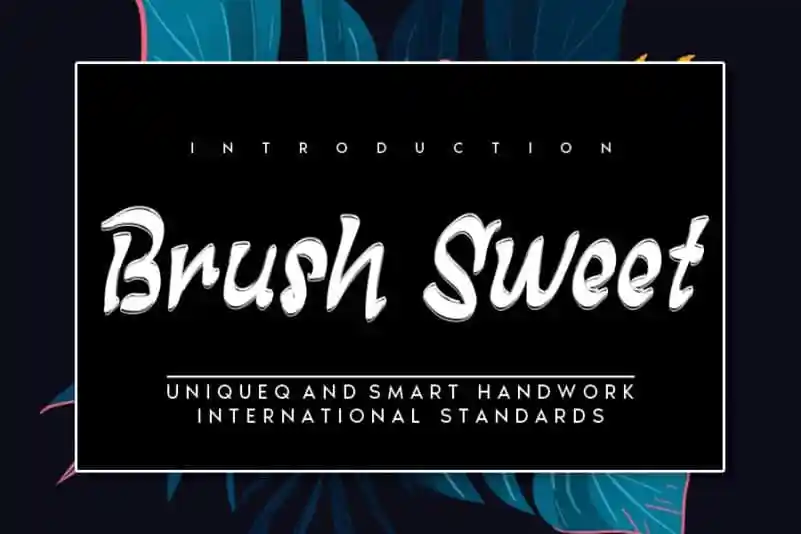
Brush Sweet Brush Font – Download Grátis
A Brush Sweet Brush Font é uma criação que resulta do apurado equilíbrio entre uma caneta a lápis e pena a pluma, criando um resultado incrivelmente encantador e autêntico. Esta elegante e única fonte de escrita à mão livre traz a mais pura essência da arte manual aos projetos do dia a dia. Se você está procurando por uma font que encaixa-se perfeitamente em qualquer DIY projeto, essa é a escolha certa para torná-lo ainda mais especial. A Brush Sweet Brush Font oferece um toque único e encantador, fazendo seu trabalho de forma impressionante. Ela é perfeita para quem busca algo que traga uma personalidade única aos seus projetos manuais, seja em gráficos, ilustrações ou até mesmo em arte digital.